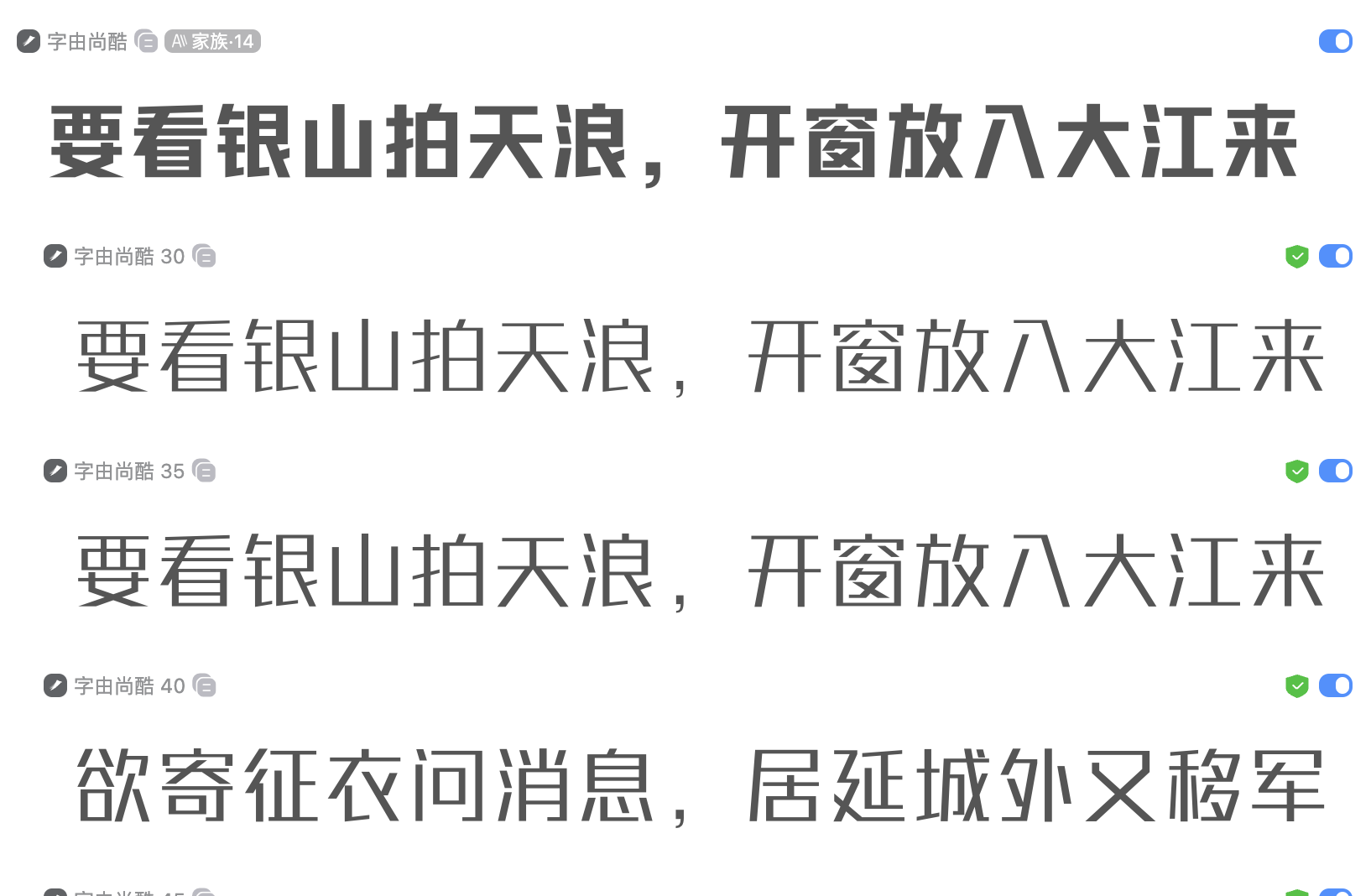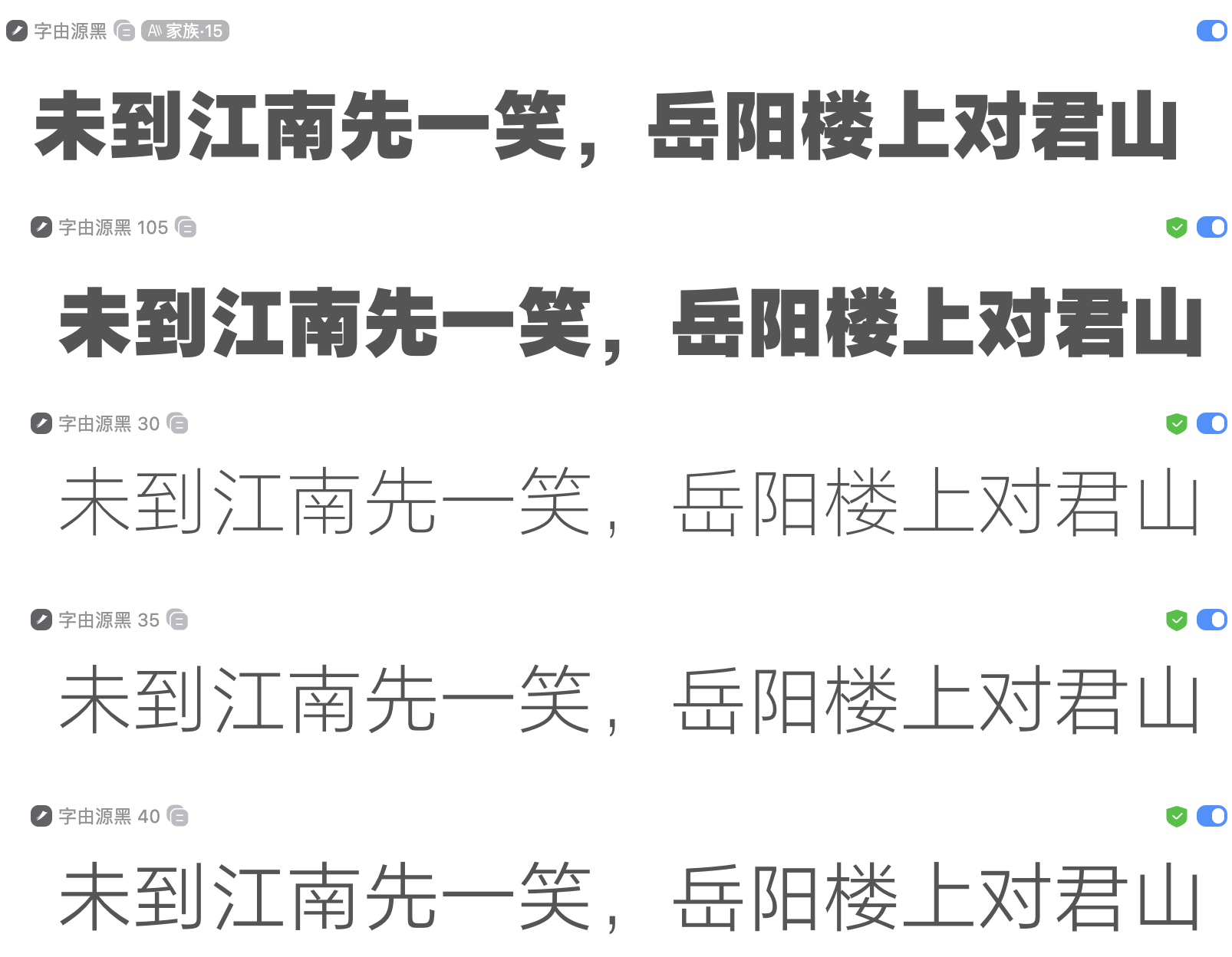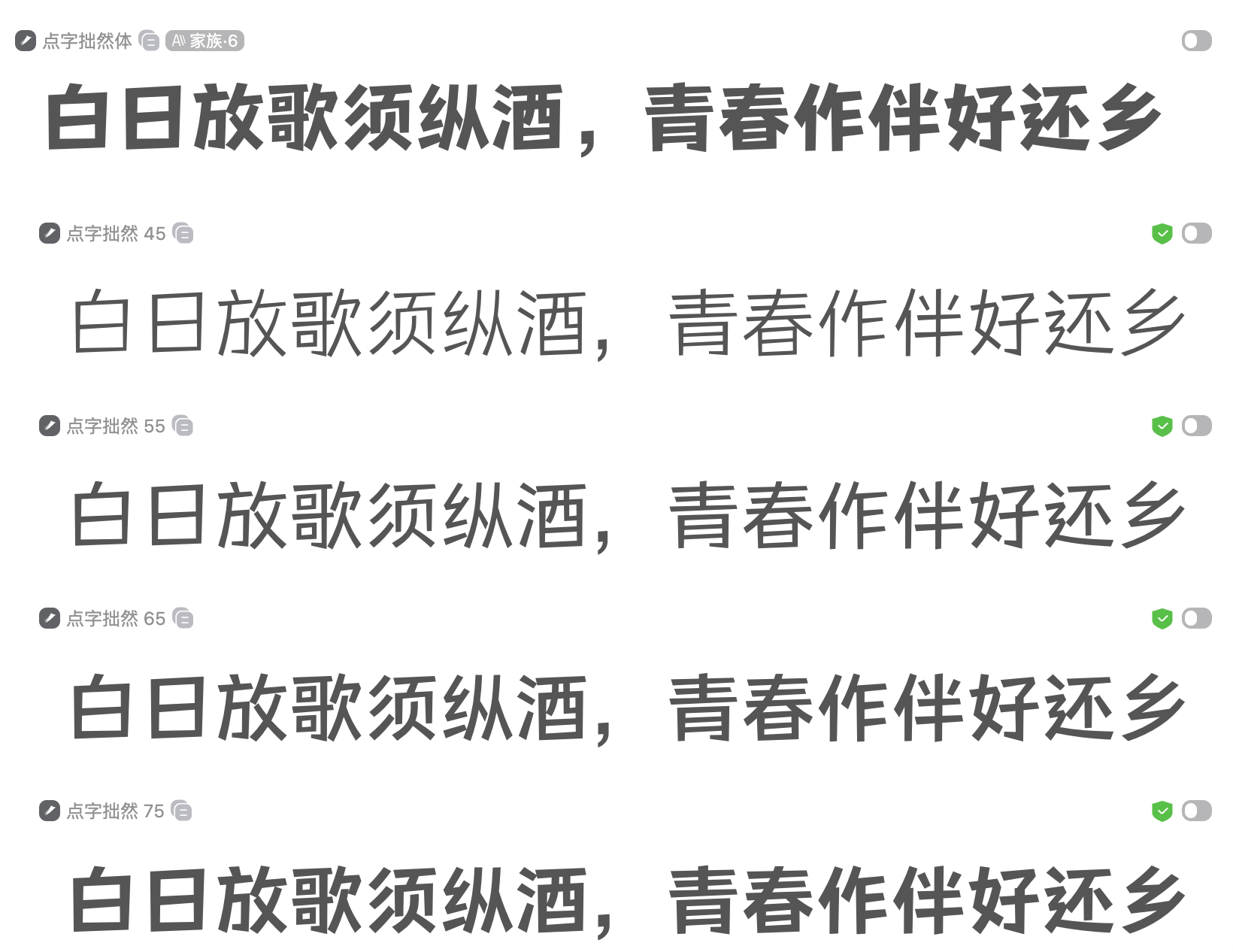
6款字体解锁电商促销设计高转化率的吸睛密码
不同于品牌宣传的温婉或艺术的含蓄,电商促销设计需要的是“直白”与“冲击”。只有这样的字体,才会让让你的网店主页和商品详情页在0.5秒内抓住用户的眼球,直接刺激点击与下单!
力量感或火热:通过粗壮的笔画和动态的字形,营造供不应求的抢购氛围。
清晰,大字易于辨认:在手机端或小图预览时,用户能瞬间识别核心卖点。去除多余的装饰,确保信息传递的效率。
今天,我们为您带来一场专为电商促销定制的字体分享,深度解析六款能瞬间点燃购物欲的强力黑体。
点字超凡战甲 - 硬核科技的爆发力
字形偏方,笔画厚重且具有明显的折角,视觉重量感极强,散发着不可抗拒的力量感。是家电、3C数码、电脑硬件等硬核科技类产品的绝佳搭档。在打造“年度旗舰”、“性能猛兽”这类充满雄性荷尔蒙的促销主视觉时,它能赋予产品不可撼动的权威感。
字由尚酷 - 极简现代的视觉切割
风格简约,去除了所有衬线和非必要装饰,只保留纯粹的几何线条。这种极致的中性风格,使其在视觉上非常“现代”。适合追求高级感和极简风的品牌,如现代极简风格的家具、高端进口产品或生活方式类店铺。它能让“全场五折”、“极简生活节”等标语显得冷静而有力。
字由源黑 - 信赖基石,稳健之选
作为一款基础黑体,其笔画粗细均匀,结构稳定,无任何多余装饰。它呈现出的是一种纯粹、冷静且高度可读的中性特质,是构建信赖感的基石。非常适合大型品牌或平台级电商(如家电、数码产品官方旗舰店)的主视觉设计。当促销活动需要传递“官方正品”、“品质保障”等可靠信息时,它能提供稳健、大气的视觉支撑,提升品牌信赖度。
点字拙然体 - 更有年轻味儿的号召
这款字体字形开张,充满生命力,有着比其他字体更年轻、放松的气质,给人一种真诚、接地气的感觉。契合“百亿补贴”、“年终清仓”、“疯狂囤货”等需要调动用户原始冲动的促销节点。它能让满减标语看起来更像是一份真诚的邀请,而非冷冰冰的广告。
优设标题黑 - 免费商用的促销利器
作为电商设计的常青树,这款字体结构紧凑,中宫收紧,富有冲击力的同时极具动感。堪称网店主页Banner和商品详情页首图的标配。特别适合用于展示价格对比、限时秒杀倒计时等需要密集排布信息的模块,稳健而不喧宾夺主。更重要的是,它是免费字体,可直接商用,性价比极高。
字由芳华体 - 免费商用的潮酷担当
这款字体带有一种独特的青春活力与潮流感。字形略微倾斜,笔画处理富有节奏感,打破了传统黑体的死板,充满年轻化的张力。非常适合面向年轻消费群体的零售产品、潮牌服饰、零食等行业的主KV设计。用它来写“618狂欢”、“潮玩新品首发”,能瞬间拉近与Z世代用户的距离,且同样支持免费商用。